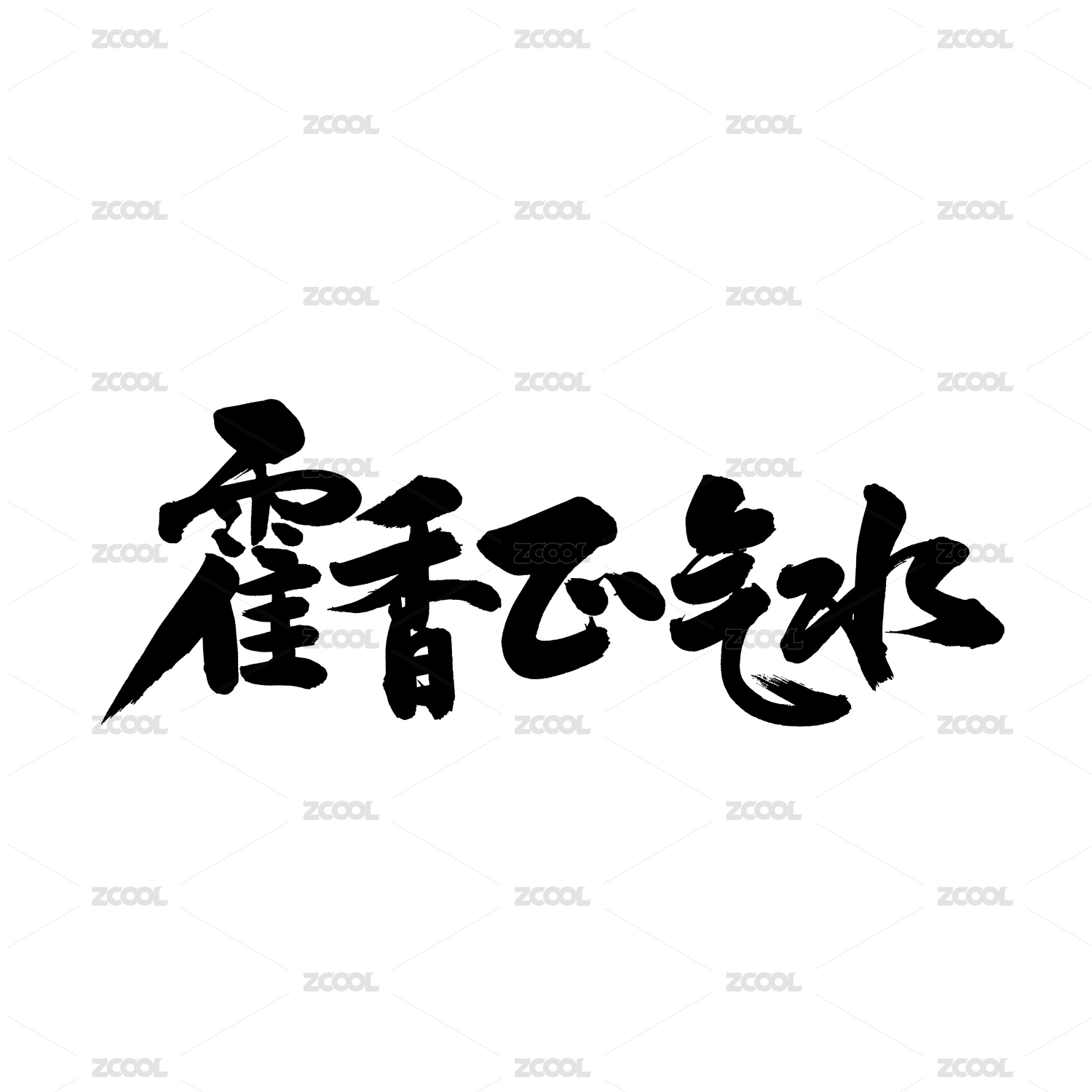
安康市青年书法家周高友作品
周高友,笔名康廙,号友子。安康市早阳人。从小酷爱书法篆刻和文学音乐。十六岁进入安康市书法协会,从事书画创作近二十年,其大部分作品被同学、老师及书法爱好者收藏。周高友先生出生于陕西安康的一个书香门第。清朝时期,周氏祖先因出仕为官,至其祖父时一直文脉不断。周氏以诗书传家,高友先生幼习书法,得其母教诲,秉承家学,临帖十余载,笔耕不辍。十二岁学治印,兼事绘画,十六岁跟随其舅舅安康著名石刻大师李典信先生学习金石篆刻,受其影响而后书法作品颇有金石之味,其书于篆、隶、行、楷、草均有涉猎,尤其擅长行书。因为热爱一直坚持,艺术的脚步从未停歇。他现在为中国书法文化研究院会员、陕西省青年书法家协会常务理事、西安市书法家协会常务理事、安康市书法家协会顾问、职业画家、艺术创作人。现出版作品有《高友书法作品集》、《高友书画作品集》。